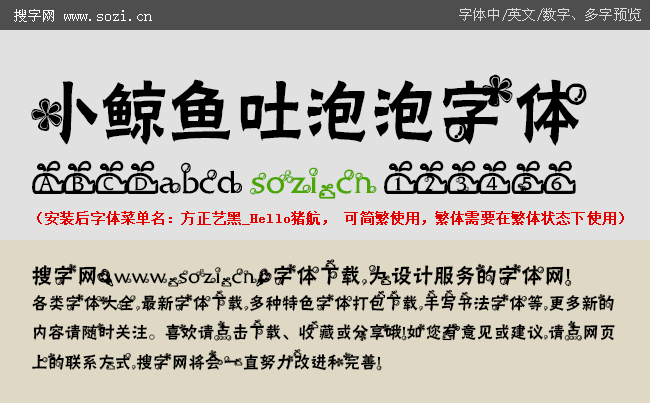
小鯨魚吐泡泡字體
搜字網(wǎng)給大家提供一款很有趣的手機(jī)中文字體下載。修改者給他起了個小鯨魚吐泡泡字體這么萌的名字,這款手機(jī)字體是在方正藝黑字體筆畫間插入了可愛的泡泡圖案。趣味性實足,該手機(jī)字體個性實足,趣味性強(qiáng),又保持了文字的識別度,特別適合喜歡手機(jī)字體個性一些的朋友在手機(jī)上安裝使用。